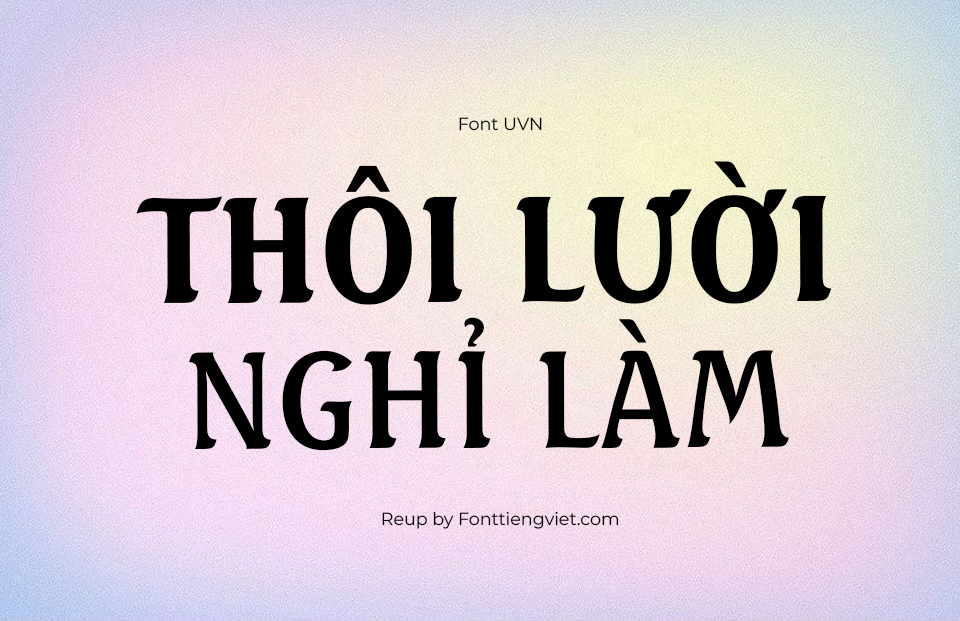
Font Việt Hóa UVN Chim Bien
Font Việt Hóa UVN Chim Bien – Lựa chọn tinh tế cho thiết kế học đường
Giới thiệu về Font Việt Hóa UVN Chim Bien
Trong thế giới thiết kế đồ họa tại Việt Nam, việc tìm kiếm một bộ Font Miễn Phí chất lượng và hỗ trợ đầy đủ tiếng Việt luôn là ưu tiên hàng đầu. Font Việt Hóa UVN Chim Bien nổi lên như một giải pháp hoàn hảo, mang đậm nét văn hóa và sự thanh thoát. Đây là một phần trong bộ sưu tập UVN nổi tiếng, được tinh chỉnh để phù hợp với các quy chuẩn gõ văn bản hiện đại. Với đường nét rõ ràng và cấu trúc cân đối, bộ font này giúp các tác phẩm trở nên chuyên nghiệp và gần gũi hơn với người xem Việt.
Đặc điểm nổi bật của Font Việt Hóa UVN Chim Bien
Tính ứng dụng cao trong giáo dục
Font Việt Hóa UVN Chim Bien sở hữu phong cách chữ thanh lịch, rất phù hợp để soạn thảo bài giảng, làm báo tường hoặc trang trí các góc học tập. Các em học sinh và thầy cô giáo có thể dễ dàng sử dụng bộ font này để tạo ra những tài liệu học tập sinh động. Nhờ khả năng hiển thị tốt trên cả màn hình và bản in, font chữ này đảm bảo nội dung luôn dễ đọc và không gây mỏi mắt.
Khả năng tương thích và tối ưu hóa
Điểm mạnh của Font Việt Hóa UVN Chim Bien chính là sự ổn định. Bạn không cần lo lắng về lỗi hiển thị các ký tự có dấu phức tạp như “ợ”, “ư”, hay “ễ”. Font được mã hóa chuẩn Unicode, giúp việc tương tác trên các phần mềm từ Microsoft Word đến Adobe Photoshop đều diễn ra mượt mà. Đây là lựa chọn lý tưởng cho những ai muốn kết hợp giữa truyền thống và hiện đại trong cùng một khung hình thiết kế.
Kết luận và trải nghiệm người dùng